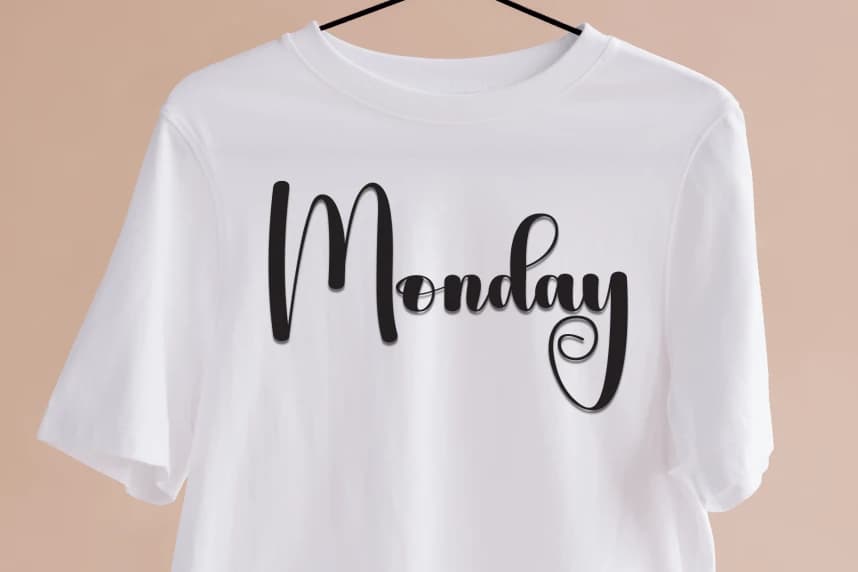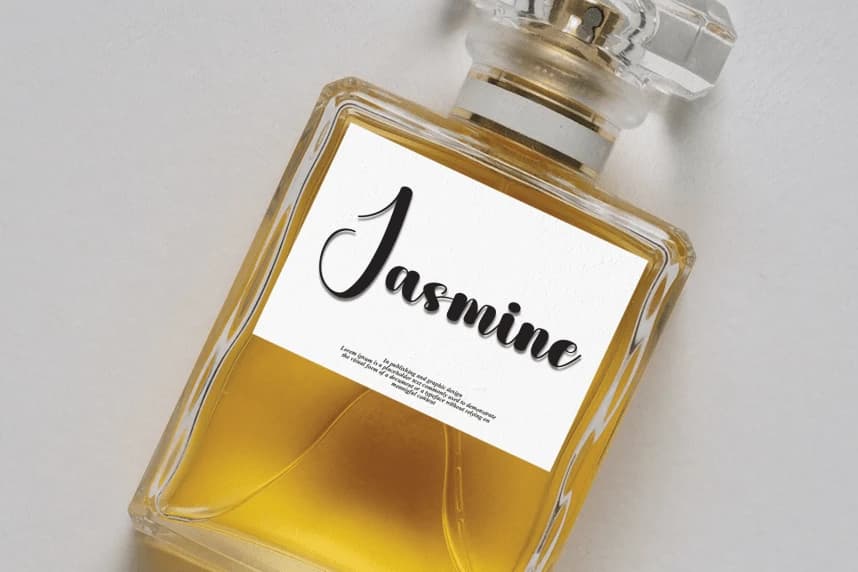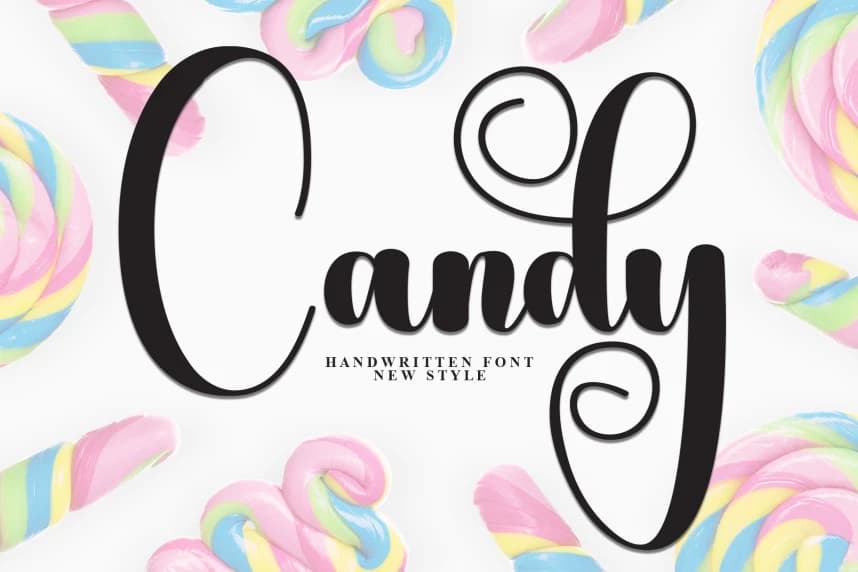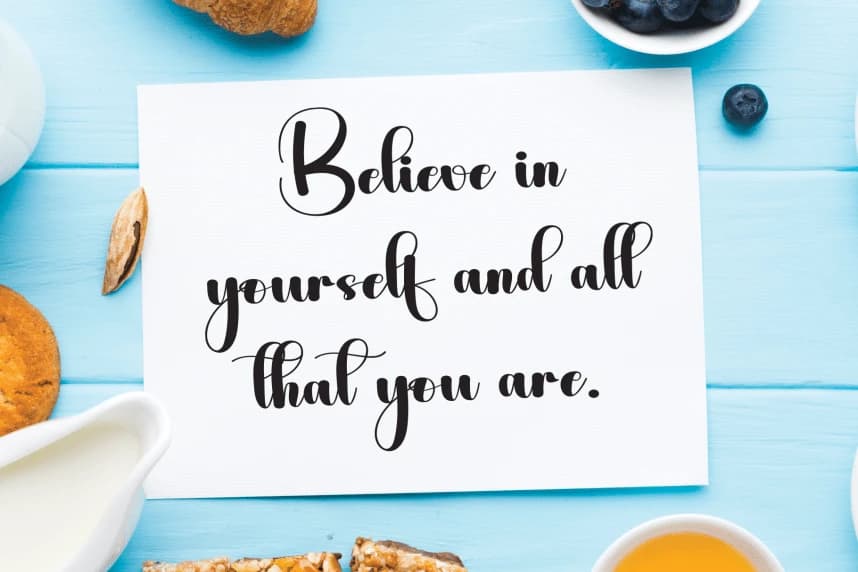
Candy – Elegant Handwritten Font, tatlı ve arkadaş canlısı bir el yazısı gösterim yazı tipidir. Sevimli ve eğlenceli olan bu yazı tipi, düğün davetiyelerini yazarken, kartlarda veya neşeli bir dokunuşa ihtiyaç duyabilecek herhangi bir tasarım için idealdir.
Candy – Elegant Handwritten Font tatlı ve dostane bir el yazısı gösterim fontudur. Sevimli ve eğlenceli olan bu font, düğün davetiyelerini yazmak, kartlar hazırlamak veya eğlenceli bir dokunuşa ihtiyaç duyabilecek diğer tasarımlar için de uygundur!